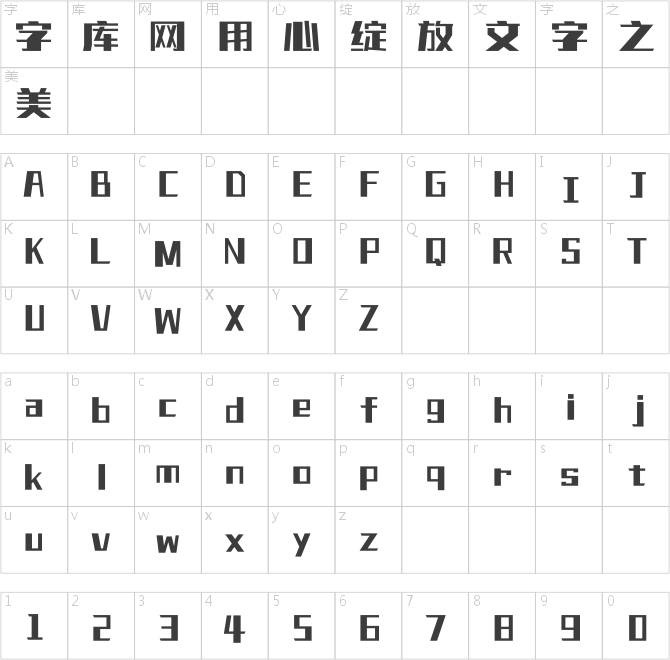
上首山川體,字體視覺效果更為有科技感,采用了橫細(xì)豎粗的做法是此套字庫的亮點(diǎn)。適用于搭配標(biāo)志、廣告標(biāo)語、商業(yè)廣告等高端屬性。
上首山川體字體字庫是一款讓人賞心悅目、百看不厭的中文字體,適合各類廣告和產(chǎn)品包裝設(shè)計(jì)應(yīng)用,字體大小1.66MB,格式為ttf字體,上傳用戶是上首造字,作者/版權(quán)方為上首造字